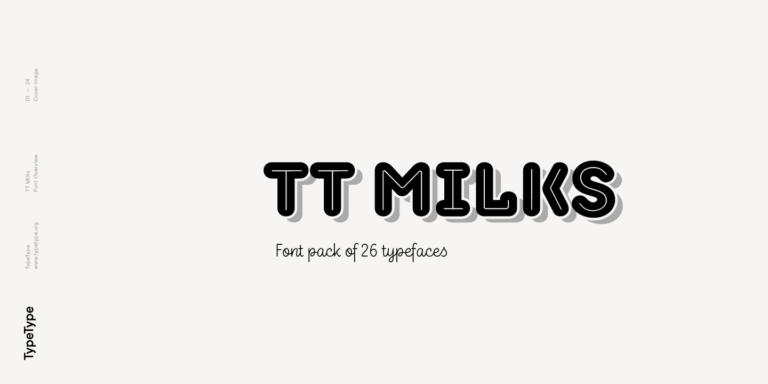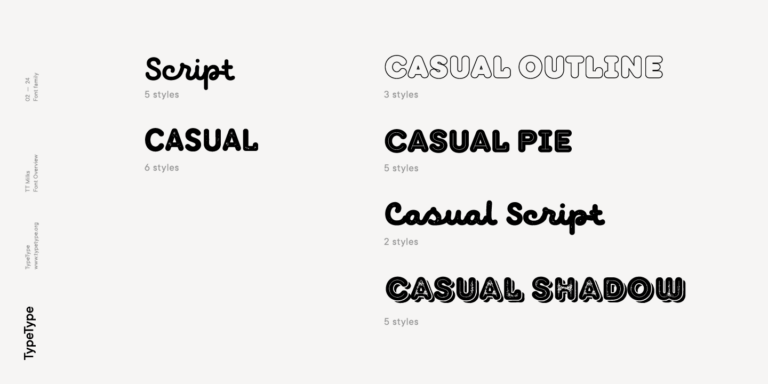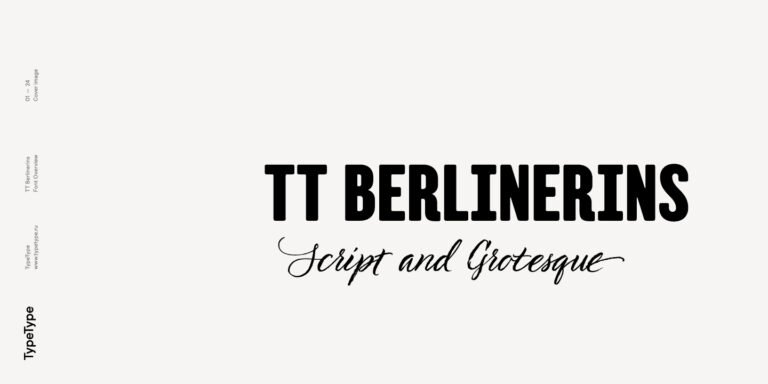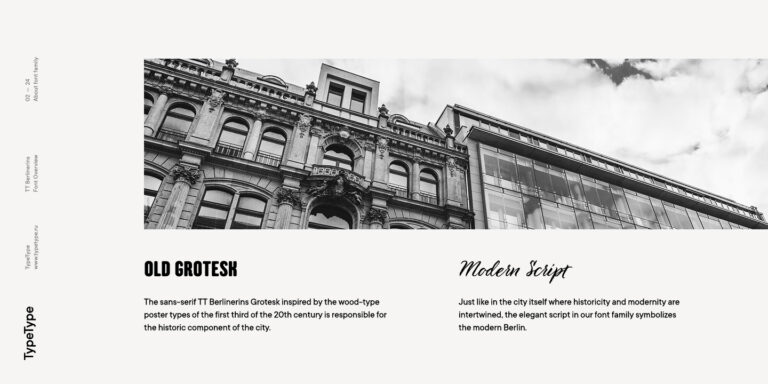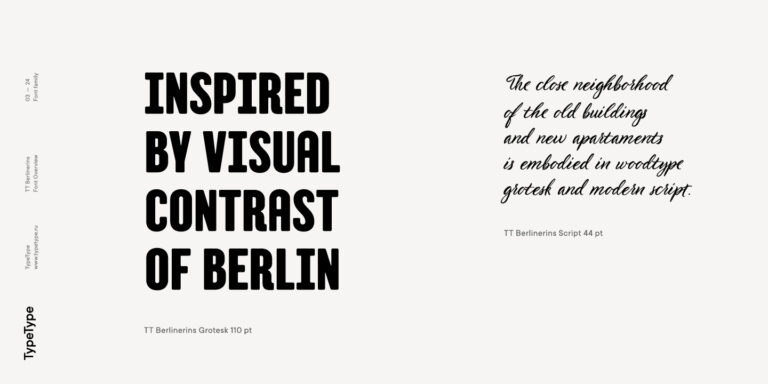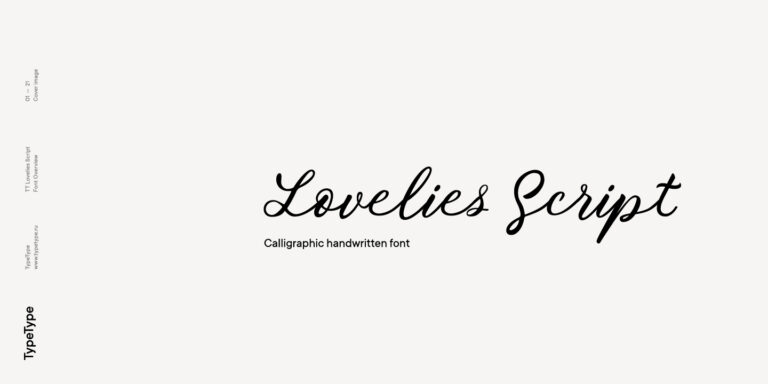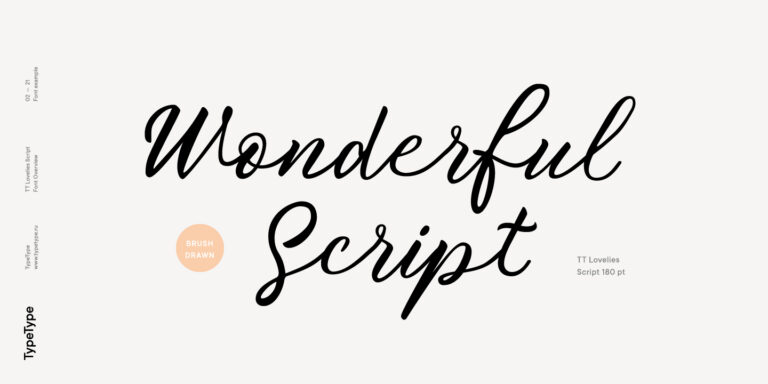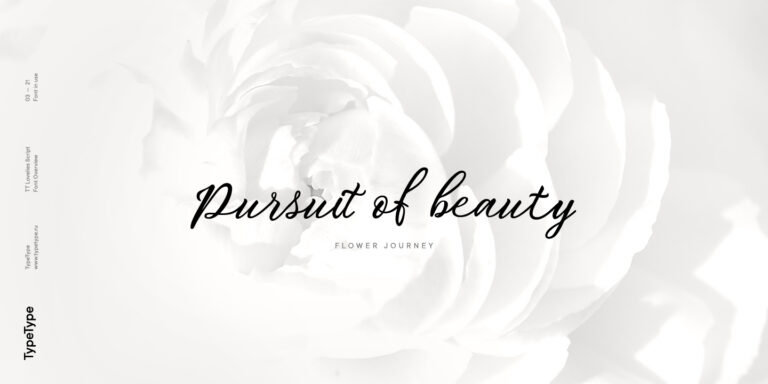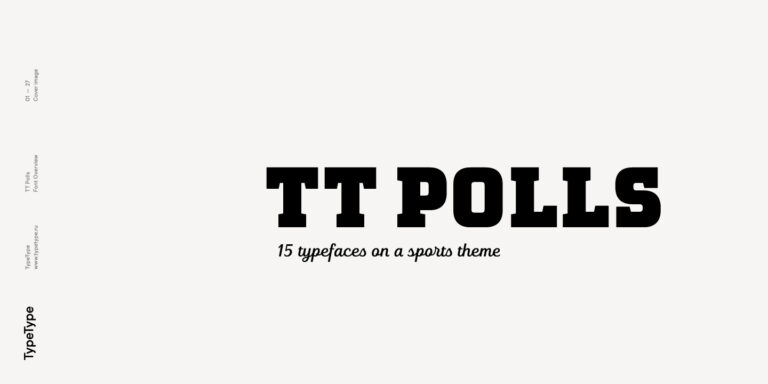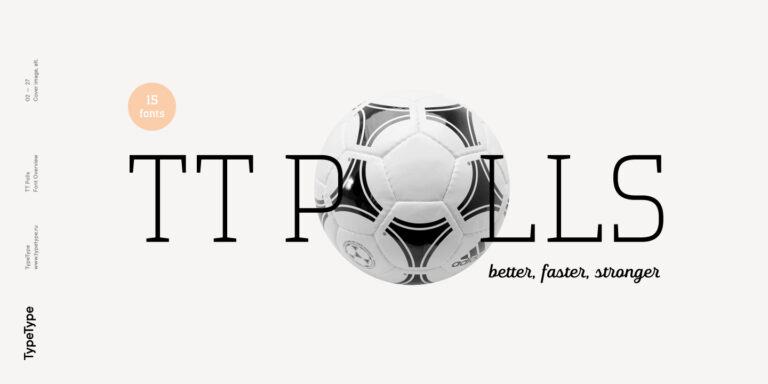
TT Nooks Serif est une serif moderne display avec une légère touche d’égocentricité. Elle possède un caractère acéré et affirmé, tout en restant élégante et majestueuse.
Polices similaires à ITC Edwardian Script
Si vous en avez assez des polices surutilisées et que vous recherchez des polices similaires à ITC Edwardian Script, découvrez nos meilleures alternatives à ITC Edwardian Script gratuites à essayer, qui présentent des caractéristiques proches ainsi que des éléments de design nouveaux et uniques. Certaines polices appartiennent à la même catégorie typographique, tandis que d’autres conviennent aux mêmes usages ou partagent des traits similaires, tout en se distinguant par leurs détails ou leurs proportions spécifiques.
Chez TypeType, vous trouverez des polices innovantes comme ITC Edwardian Script, et même mieux : voici une sélection d’alternatives à ITC Edwardian Script remarquables et moins répandues. Utilisez cette liste de polices de haute qualité similaires à ITC Edwardian Script selon vos besoins. Notre sélection offre un éventail plus large d’options pour choisir la meilleure police pour votre projet et renouveler vos designs. Toutes les polices présentées dans cette collection sont disponibles dans plusieurs formats et à des prix accessibles, afin de répondre à tous vos besoins !
Trouvez une excellente police de remplacement pour ITC Edwardian Script et essayez de recréer une ambiance similaire ainsi que l’émotion souhaitée en l’utilisant dans vos designs. Chaque police présentée sur cette page est une alternative à ITC Edwardian Script, avec une apparence très proche.
TT Backwards Sans est une grotesque étroite dont les caractères souples nous ramènent au design éditorial de la fin des années 1970 et du début des années 1980.
TT Knickerbockers Grotesk est une sans serif étroite et contrastée dont les éléments caractéristiques nous replongent dans le New York du XIXe siècle.
TT Polls est une famille slab serif modulaire moderne conçue pour le design sportif.
TT Berlinerins est une grotesque inspirée des caractères en bois utilisés sur les affiches du premier tiers du XXe siècle et représente la composante historique de Berlin.
TT Milks est une collection de typographies destinée au branding.
Sans fausse modestie, nous pouvons dire que TT Lovelies Script est l’un des projets les plus complexes que nous ayons jamais réalisés : cette police comprend 1115 glyphes, plus de 2000 variantes contextuelles, 10 000 paires de crénage et un grand nombre de fonctionnalités OpenType, dont des ligatures et des chiffres elzéviriens.